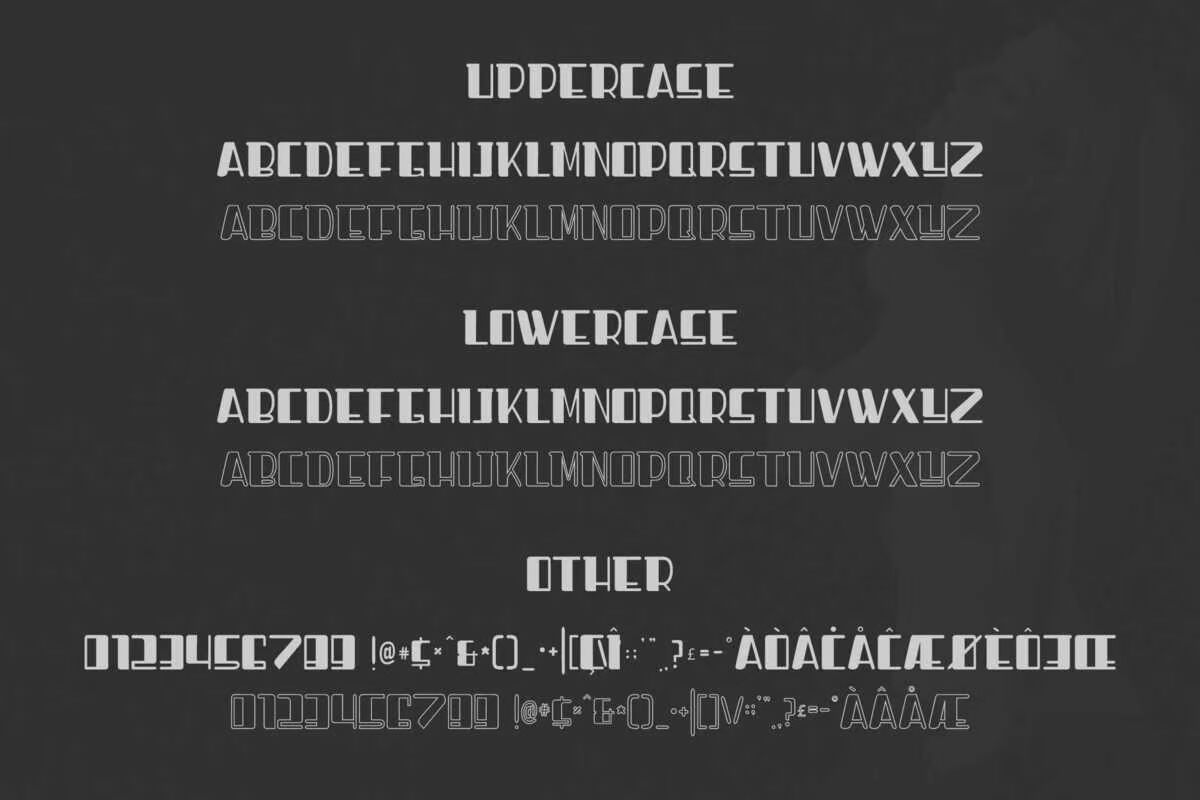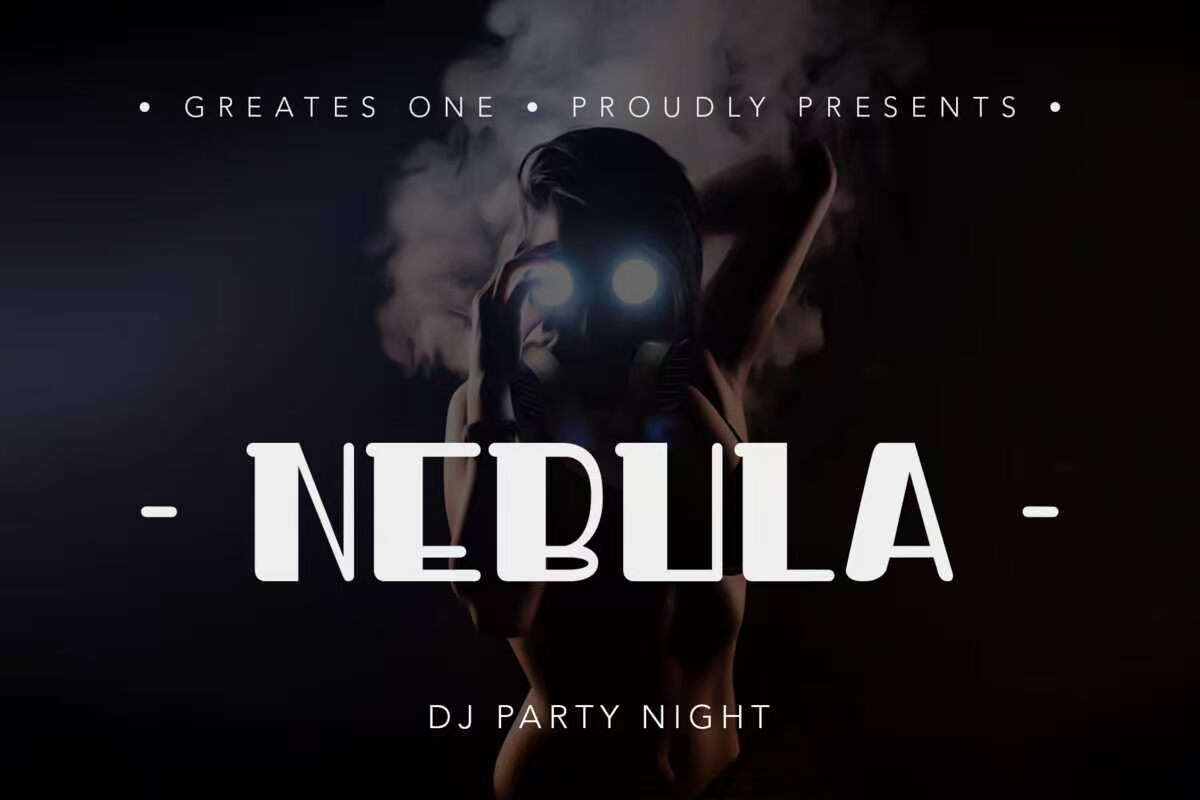
DjakartaMinimalistDisplayFontStrongandEnLinerm,具有输出和RegulerVersion。通过IsStrongPersonality激励。DjakartaMinimalistDisplayFontStrongandEnLinerm,具有输出和RegulerVersion。通过IsStrongPersonality激励。DjakartaMinimalistDisplayFontStrongandEnLinerm,具有输出和RegulerVersion。通过IsStrongPersonality激励。